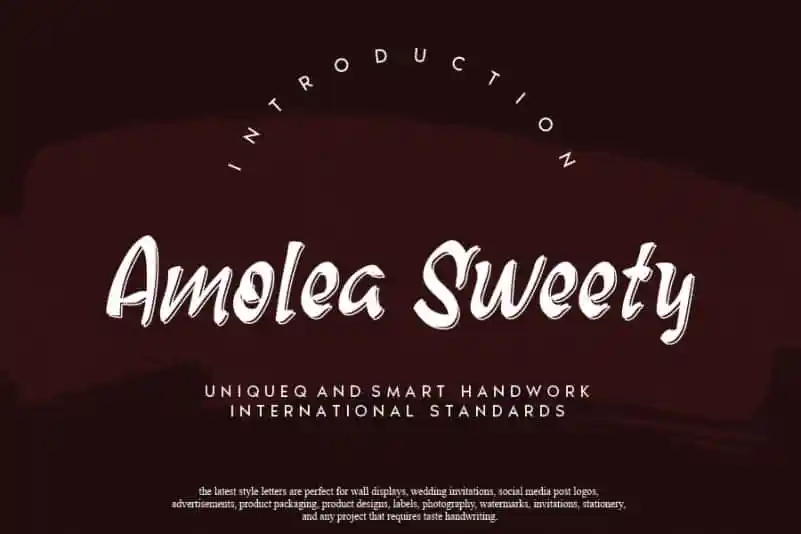
Amolea Sweety Script Font – Download Grátis
Amolea Sweety Script Font é uma linda fonte cursiva perfeita para ambientes digitais que valorizam a simplicidade e o charme. Trabalhada com mão, esta fonte adquire um ar natural, despojado e fácil de ler. Suas características tornam-na versátil, capaz de adaptar-se em diversos contextos, seja para uso em fundos atarefados ou como destacamento na página. Seja você um designer criando um layout dinâmico ou um blogueiro buscando uma fonte que ressalte seu conteúdo, Amolea Sweety é a escolha perfeita para tornar sua mensagem ainda mais envolvente e autêntica. Seu estilo casual é encantador e permite que o texto fique ao nível de quem está lendo. Sua elegância natural faz com que cada caractere seja uma obra de arte em si, sem parecer exagerado ou fraco. É um recurso gráfico perfeito para qualquer designer que busque transmitir uma mensagem mais acessível e emocionalmente conectada, criando um impacto visual atraente nas páginas dos seus projetos.